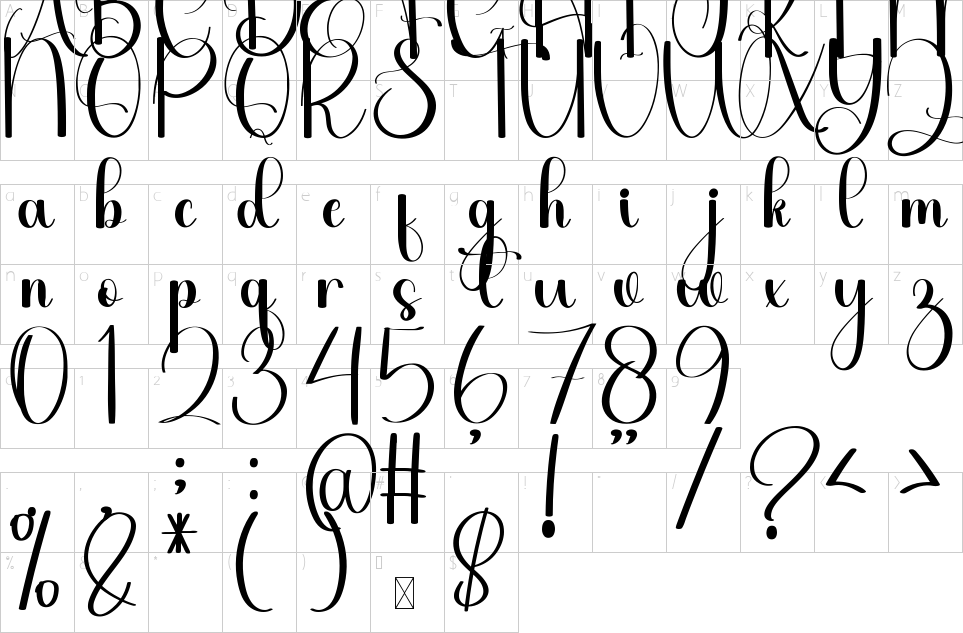
Descubra a caligrafia delicada e elegante da Daddy Handwriting Font, perfeita para adicionar um toque autêntico e envolvente aos seus projetos digitais. Esta font foi criada pelo produtivo Designer InermediaSTUDIO e tem sido uma opção popular entre designers que buscam expressar emoções através de textos manuscritos. Com traços suaves e linhas leves, esta caligrafia representa um estilo único que combina facilmente com qualquer projeto. Seja para criar cartões personalizados ou designs digitais de alta qualidade, a Daddy Handwriting é uma opção incrível para quem busca uma fonte impecável sem ter que investir em um design de letra. Ainda não se convencido? Imagine seus projetos digitais transformados por esta caligrafia delicada e elegante. Quer você esteja criando cartazes, infográficos ou simplesmente adicione um texto ao seu site pessoal, a Daddy Handwriting terá o poder de fazer sua obra trazer aos olhos do espectador uma sensação de envolvimento emocional. Esta font vem em versões para Windows e Mac, permitindo que você use suas habilidades criativas no ambiente da sua escolha. Não hesite mais: baixe agora a Daddy Handwriting Font e experimente essa fonte que vai fazer a diferença na forma como você expressa seu design digital.